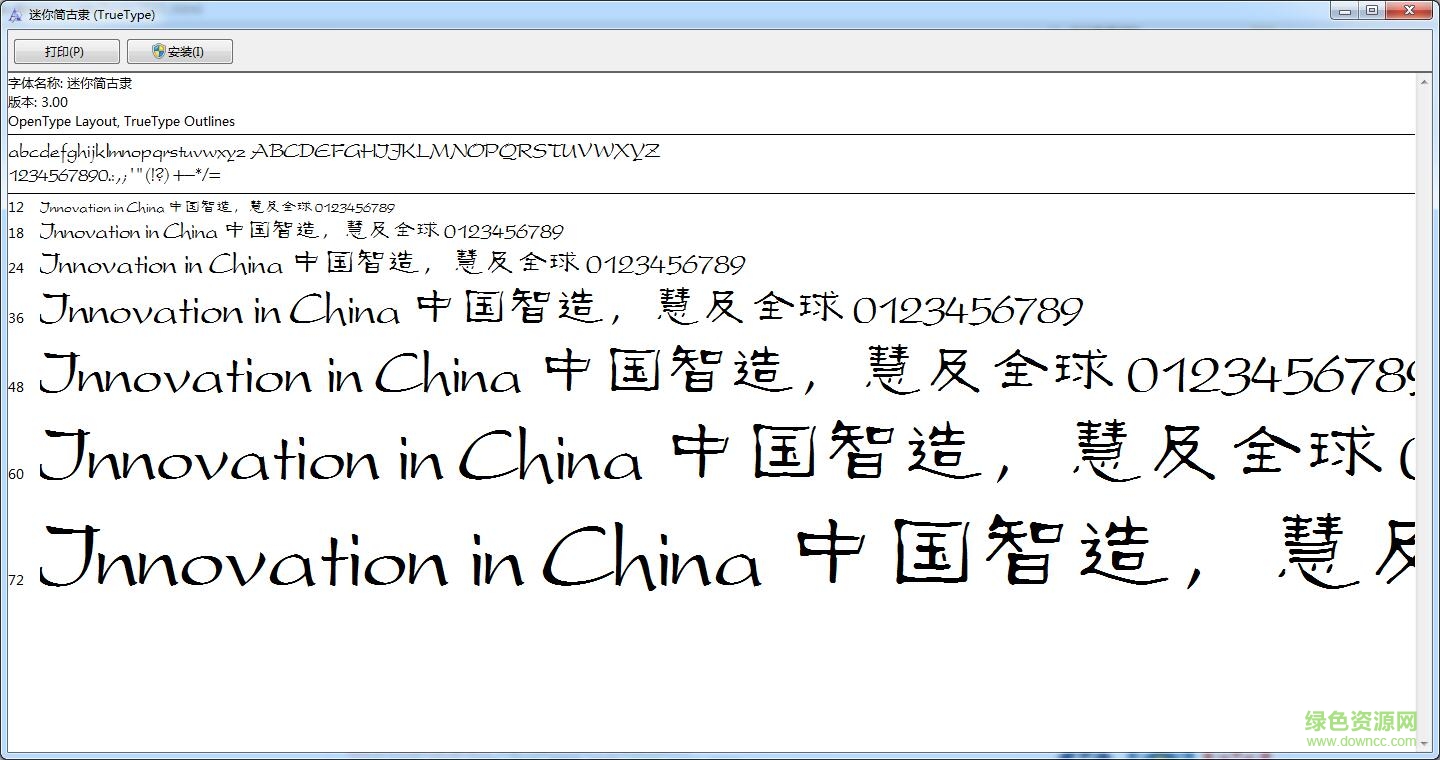
jguli字體
jguli是什么字體?jguli字體又叫迷你簡(jiǎn)古隸字,是一款線條比較隨意的隸書字體,筆畫虛實(shí)相兼,疏密得當(dāng),比一般的隸書字體更靈動(dòng),極具神韻,雖然極具特色,但是一般只有在特殊的書籍中才會(huì)有使用,如果你需要,那就登陸綠色資源網(wǎng)下載使用吧!
隸書字體介紹
隸書:好的書法作品中,隸書含中有露、剛?cè)岵?jì),是很雅的一種,表現(xiàn)力十分豐富,可惜在中國(guó)內(nèi)地活字印刷年代制造的隸書字圓潤(rùn)有余、力度和變化不足,電腦排版時(shí)代的隸書字體完全沿用了那種隸書,后來(lái)才出現(xiàn)的毛隸、隸變(小隸)等隸書字體書法韻味有所改進(jìn),但仍缺乏變化。不適合大篇幅使用。